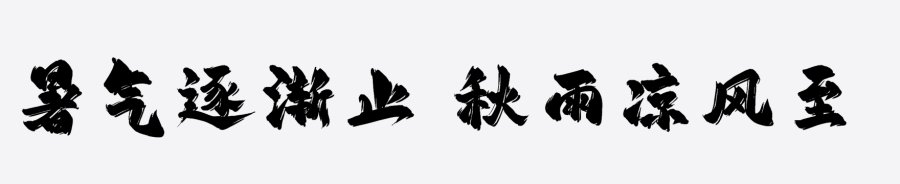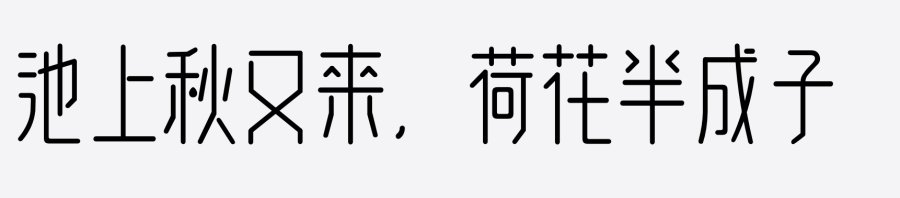
处暑海报字体素材有哪些?
处暑即出暑,意味着炎热酷暑的结束,暑气逐渐止,秋雨凉风至。
在农历二十四节气之中的第14个节气处暑的设计海报中,你是否还在为用字发愁,别急,字体视界已经为您整理好了关于处暑节气的用字,一起来看看吧。
平方飞扬体是一款不错的艺术字体,自带毛笔飞白效果的书法艺术字体,很好的视觉感。适合应用于艺术设计、平面宣传设计、网页设计等领域。
平方飞扬体
逐浪蜜蒙润楷体字体纤长、偏瘦,字体多有圆点结构,简洁但不重复累赘,用于表现可爱、温柔的元素,追求字体的严谨表达。
逐浪蜜蒙润楷体